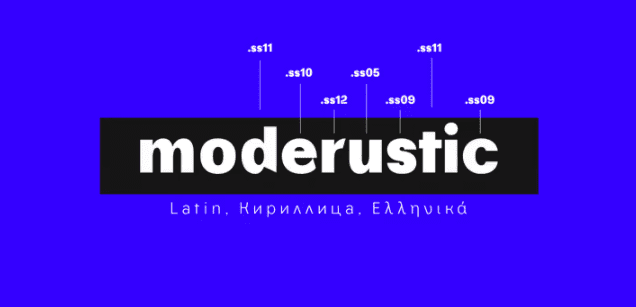
Название: TA Moderustic Font Family (2021)
Для обеспечения удобного чтения на большинстве языков TA Moderustic имеет огромную языковую поддержку, включая почти все латинские языки, греческий и кириллицу. Помимо обширной языковой поддержки, TA Moderustic имеет стилистические наборы (ss01-15) для современного дизайна UI/UX.